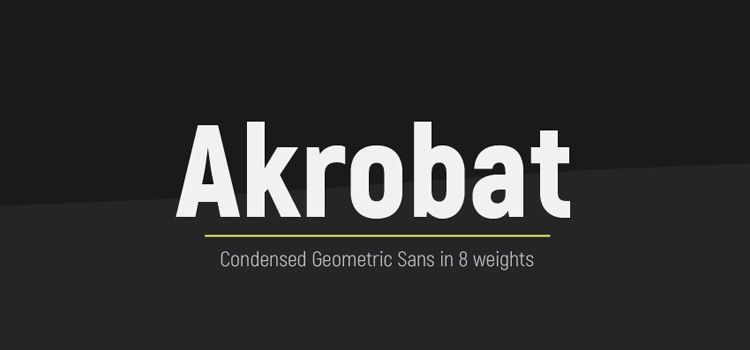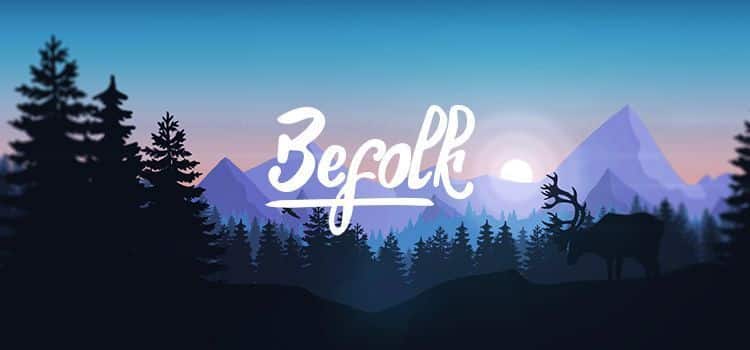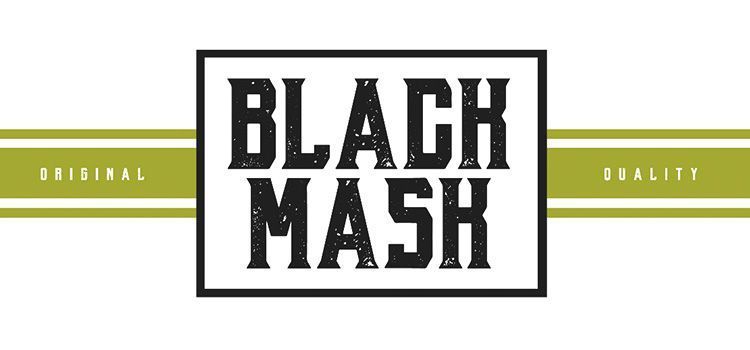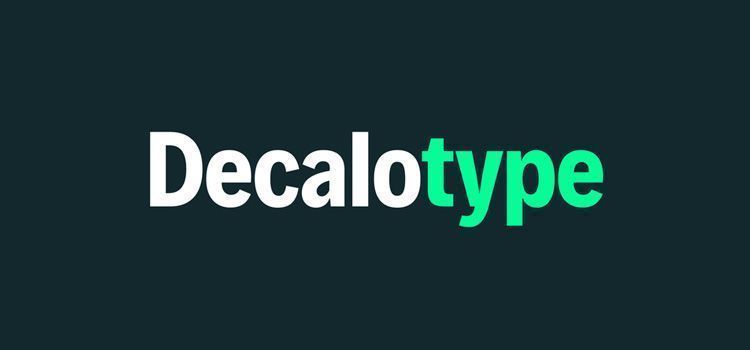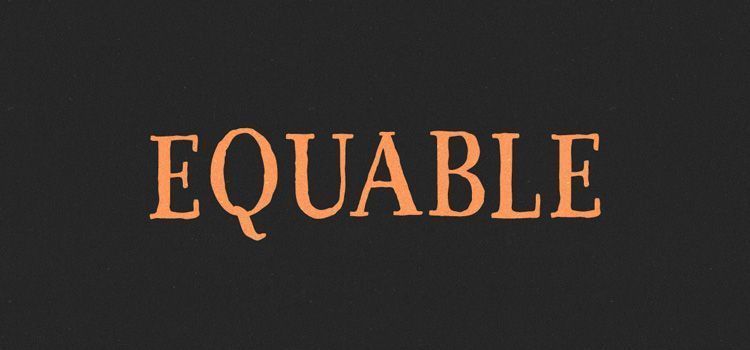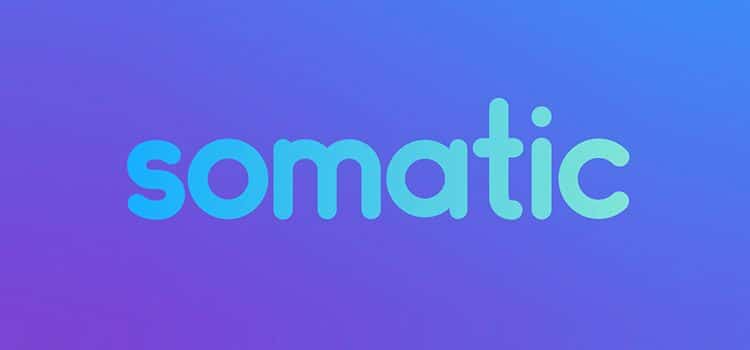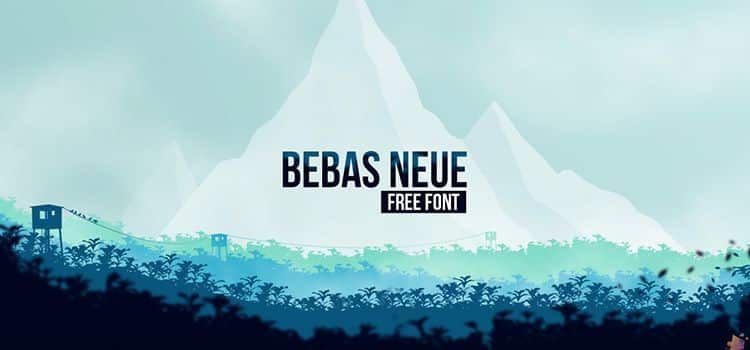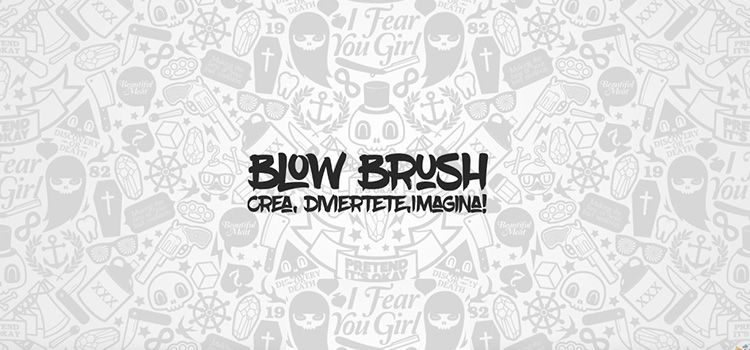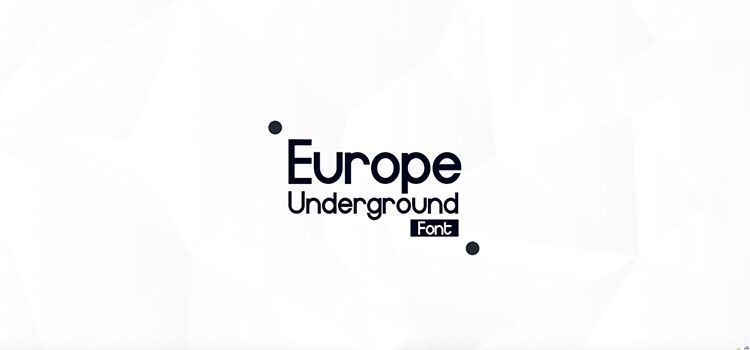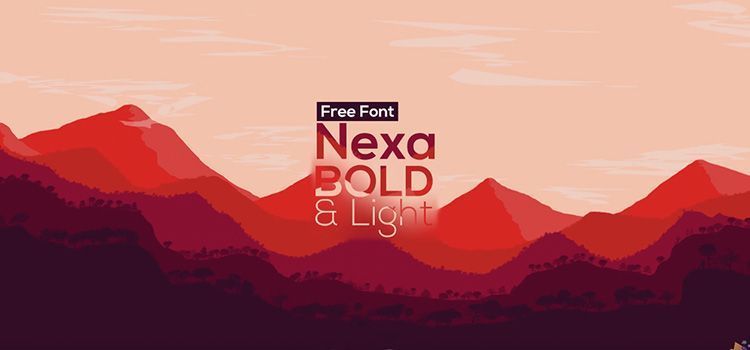
Las diez mejores tipografías gratuitas de 2017
Tipografías Gratuitas de 2017
Una fantástica selección con las diez mejores tipografías gratuitas de 2017.
Gracias a la globalización son más los profesionales que deciden compartir sus creaciones con la comunidad y así buscar su propio camino en el competido mundo del diseño. Y es que el mundo de la tipografía ha cambiado mucho desde Max Miedinger inventara la Helvetica, o Adrian Frutiger hiciera lo mismo con la tipografía Futura.
La globalización y la democratización del diseño a causa de la irrupción de internet ha saturado la red de tipografías. Esto ha llevado a los diseñadores actuales a trabajar con pocas tipografías para no perder tiempo buscando entre tantas opciones. Prueba de ello son las diez mejores más utilizadas por los diseñadores o las diez mejores tipografías utilizadas en diseño web. Tan presentes en nuestro top5 mensual de las notícias más leídas en el blog de la Eslogan Magazine.
Hoy vamos a repasar las diez mejores tipografías gratuitas de 2017.
Bebas Neue
Tipografía Bebas Neue
Diseñada por Ryoichi Tsunekawa, la Bebas Neue se consideró la ‘Helvetica de las tipografias gratuitas’. Ahora se ha convertido ahora en una familia completa -Thin, Light, Book y Regular y se ha convertido en una de las fuentes más descargadas de 2017.
Nexa Font
Tipografía Nexus
La familia tipografía Nexa se caracteriza por una excelente legibilidad tanto impresa como en la web. Con un diseño geométrico bien acabado y un interletraje optimizado, Nexa es más adecuado para titulares de todos los tamaños. Una fuente perfecta para funcionar en cualquier campo: web, motion graphics, o pósters.
Europe Underground Font
Tipografía Europe
Diseñada por Mans Greback, la Europe Underground Font quiere imitar la tipografía de las señaléticas de los metros europeos. Una fuente versátil que servirá para titulares, cartelerías y señaléticas.
Befolk font
Tipografía Befolt
La Befolk Brush Script es una tipografía manuscrita con un poco de bold. Una tipografía que se puede utilizar en multitud de sitios y mezclarse con otras fuentes para crear mensajes atractivos.
Blow Brush Font
Tipografía Blow Brush
Blow Brush es una tipografía manuscrita inspirada en la cultura hip hop y la comunidad del graffiti. Con letras legibles y muchas variaciones es una tipografía apta para todo tipo de público.
Black Mask Font
Tipografía Black Mask
La tipografía Black Mask es una fuente inspirada en la época de Giemons. Black Mask tiene un estilo de prensa con un efecto de textura. Excelente para una amplia gama de proyectos.
Somatic Font
Tipografía Somatic
La tipografía Somatic es una fuente diseñada por la diseñadora e ilustradora Lauren Lee. Se caracteriza por una estructura simple y bordes redondeados, ideal para logotipos simples.
Equable Font
Tipografia Equable
La tipografía Equable es una tipografía hecha a mano muy elegante, con curvas naturales imperfectas, pero que se ve agradable y ordenada. Una fuente de estilo vintage que coincide con la tendencia de diseño actual.
Decalotype Font
Tipografía Decalotype
La tipografía Decalotype es un sans serif multiusos, estrecha y robusta. Con más 14 estilos.
Akrobat Font
Tipografía Akrobat
La tipografía Akrobat está diseñada por Plamen Motev y es una fuente sans serif moderna con proporciones condensadas. Sus estrechas proporciones la hacen perfecta para titulares, logos, composiciones tipográficas y breves párrafos de texto. Akrobat contiene más de 500 glifos con una amplia gama de idiomas: compatibilidad con caracteres latinos y cirílicos ampliados, así como características de localización búlgaras.